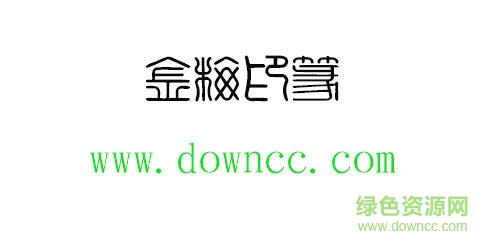
金梅印篆體字體是一款金梅類篆體字體軟件,篆體字給人非常清晰高大上的感覺(jué),而且此字體所變現(xiàn)的形式也非常具有特色,用戶們也能用它來(lái)書寫文字或者進(jìn)行廣告平面設(shè)計(jì),實(shí)用又方便,感興趣的用戶就快來(lái)綠色資源網(wǎng)下載使用吧!
金梅印篆體是金梅字體中的一種類型的字體,它以古代文字的書寫形式所表達(dá)的,能讓你的文章也能表達(dá)出樸素的感覺(jué),喜歡篆體字體的朋友可以下載使用看看效果如何。